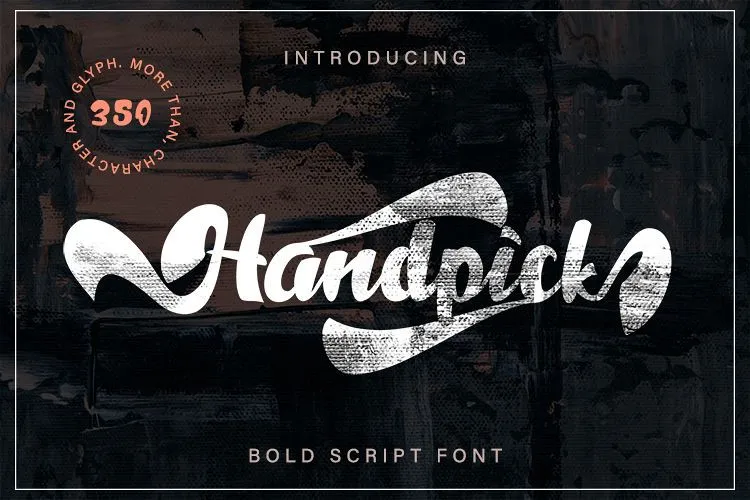
Handpick Bold Script Font – Download Grátis
Esta é uma fonte Script Bold que foi criada com o estilo do traçado manual, proporcionando um resultado firme e suave. Inspirada em traçados manuais, logotipos bold e fuentes de crianças! Introduzimos a Fonte Handpick. É uma fonte bold script poderosa e única. O Handpick vem com muitas alternativas, totalizando 356 caracteres e grafismos. Esta elegante fonte é perfeita para projetos de marca, logotipos, posters, roupas, websites, anúncios, revistas, canais no YouTube, jogos e muito mais. É uma opção divertida e única para aqueles buscando um traçado aveludado que se destaca em seus projetos visuais. Tente a Handpick Bold Script Font para seu próximo projeto.